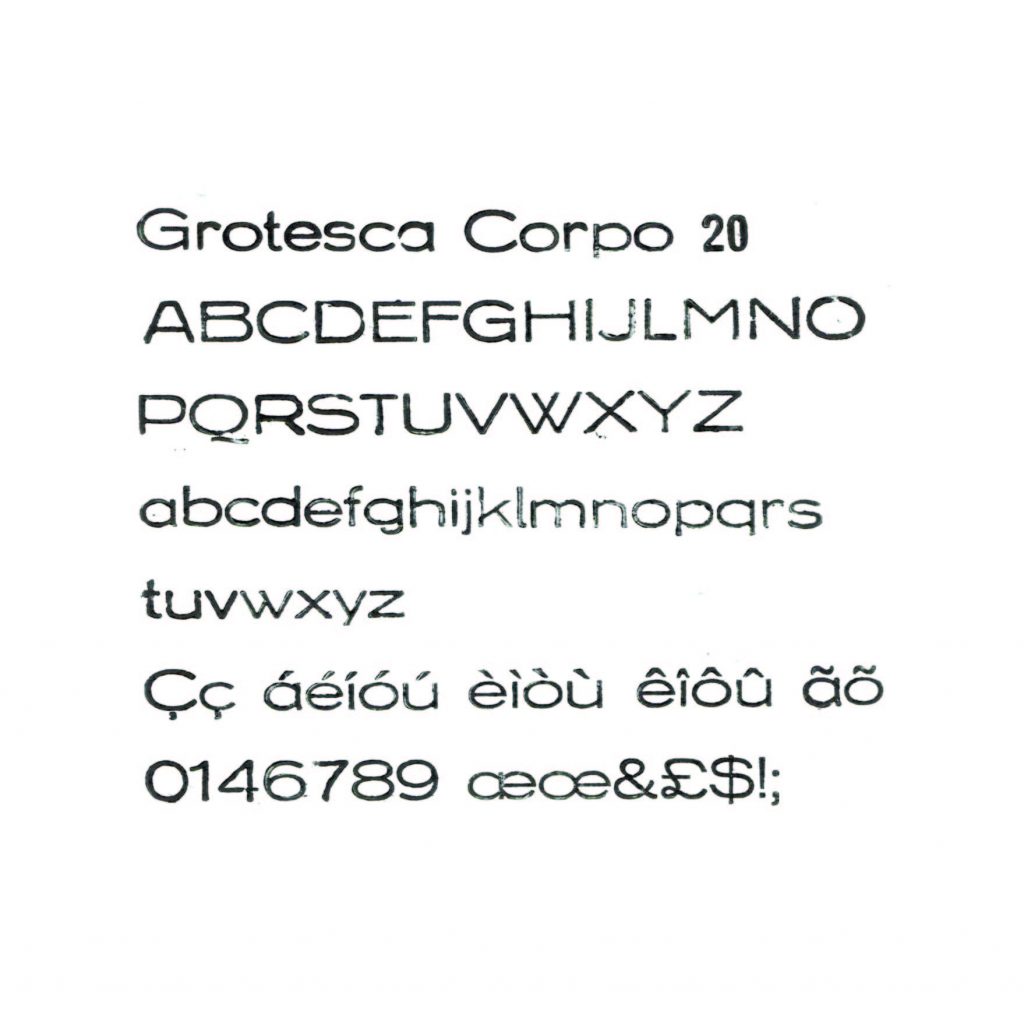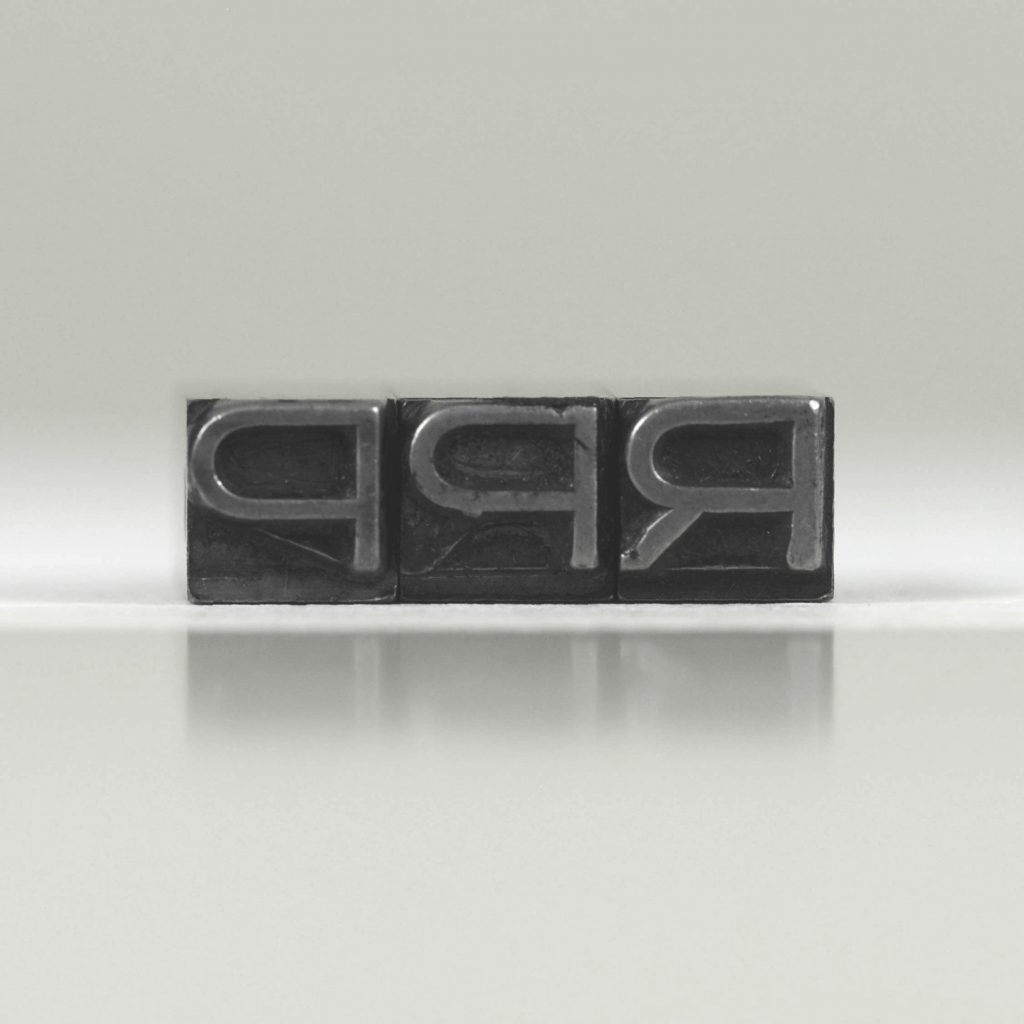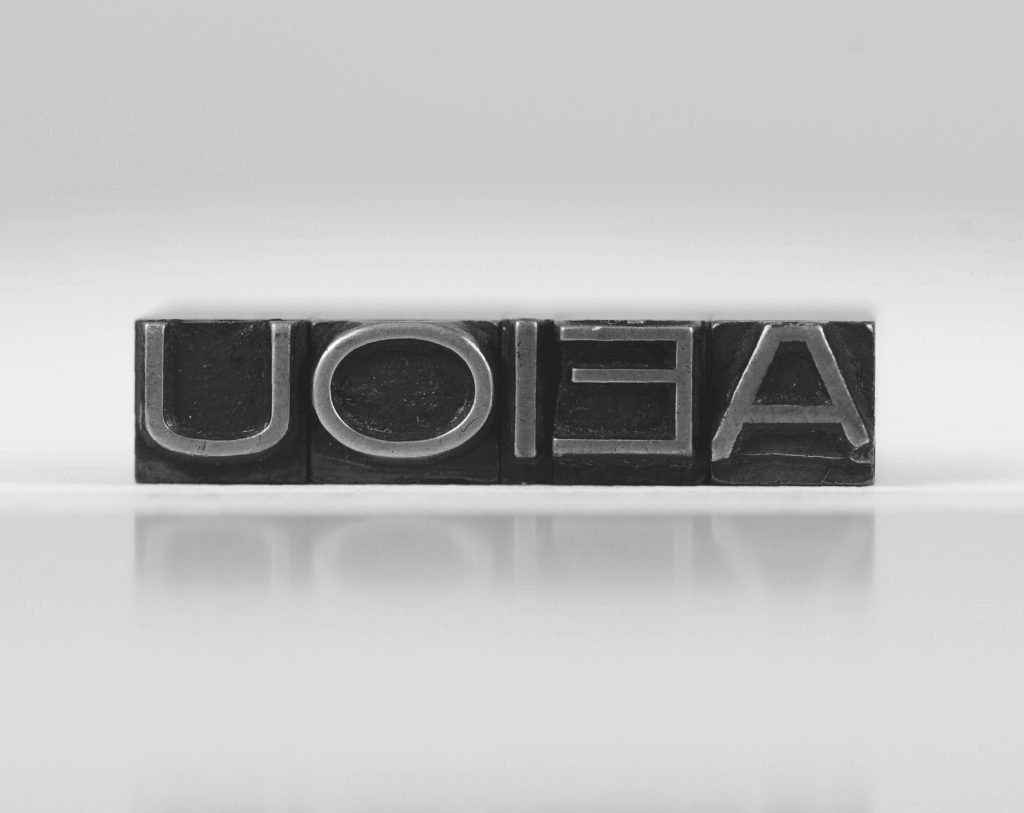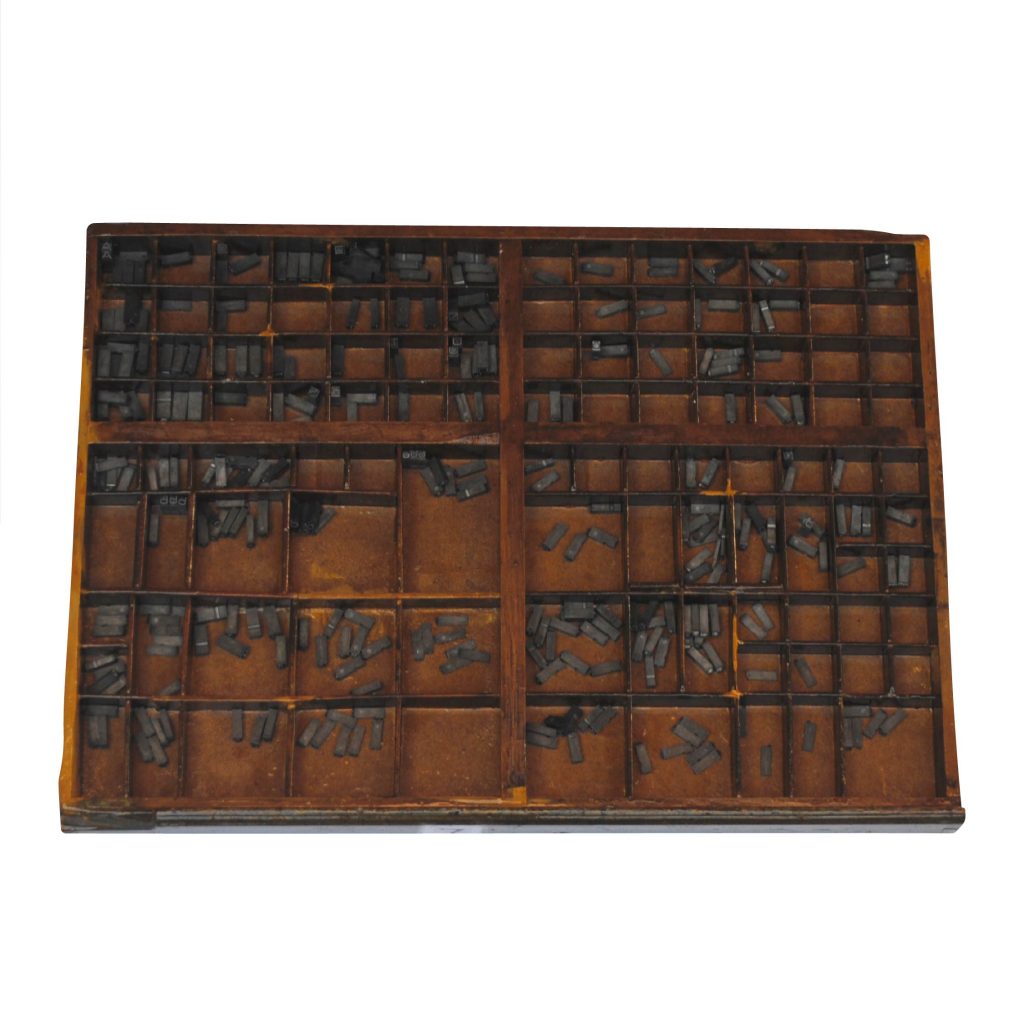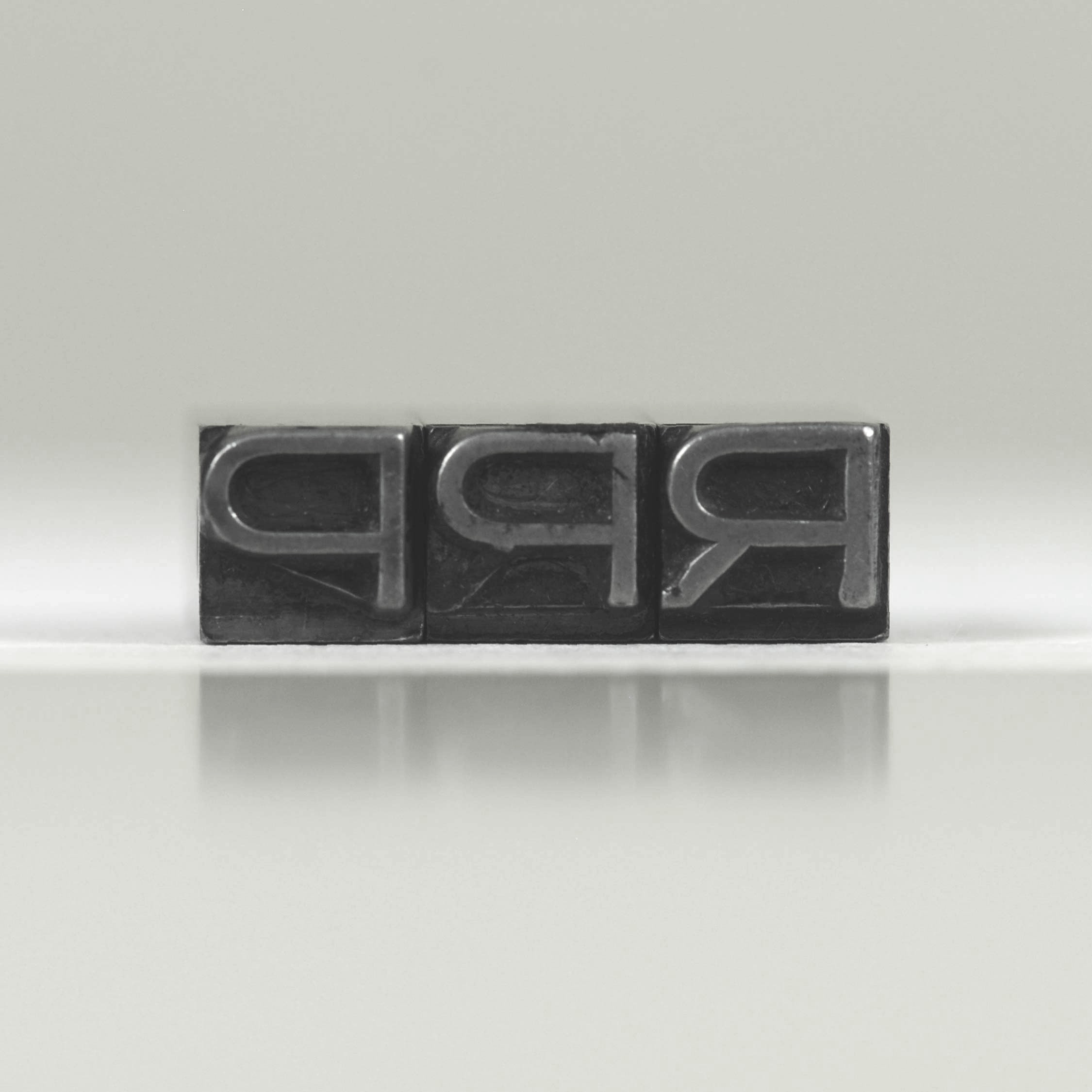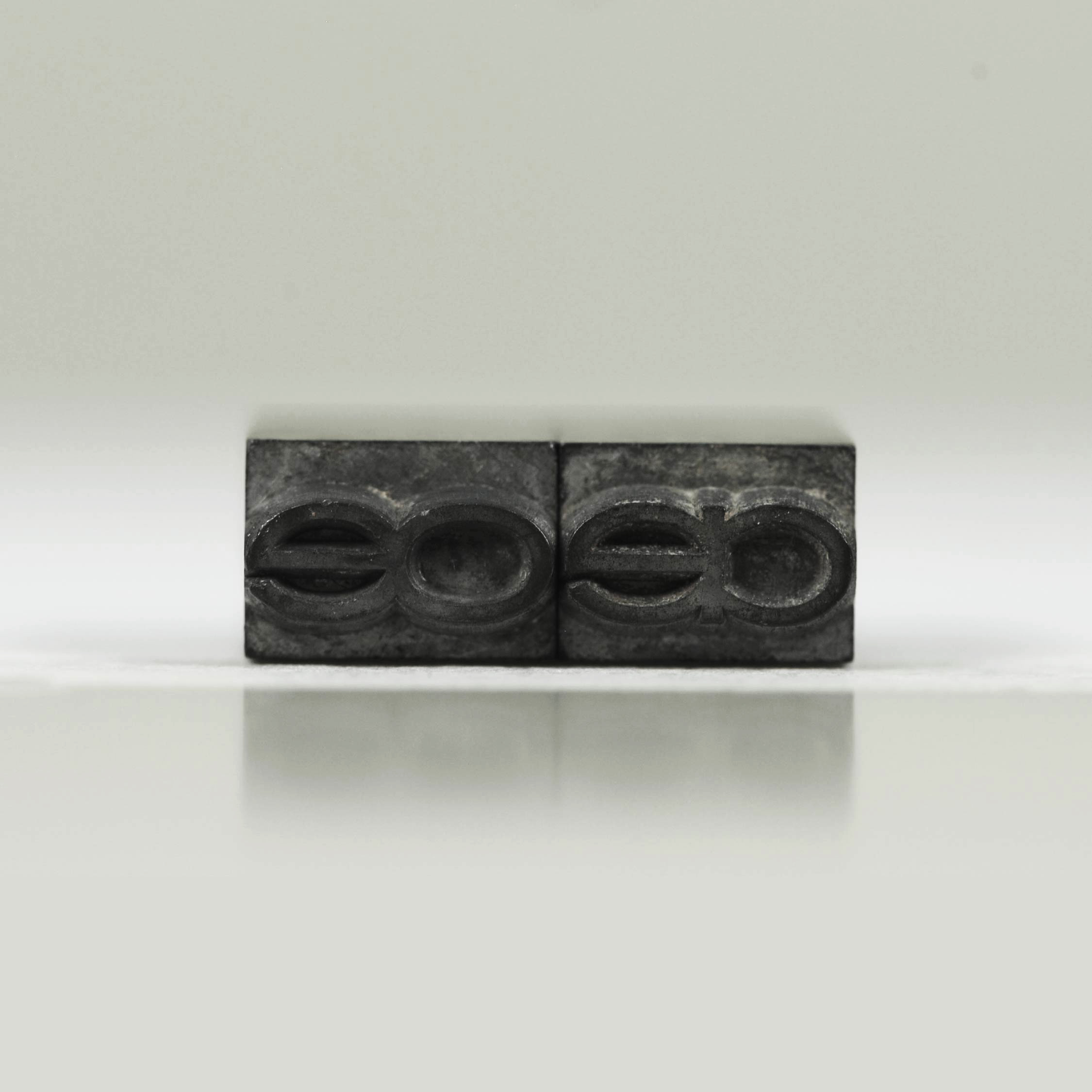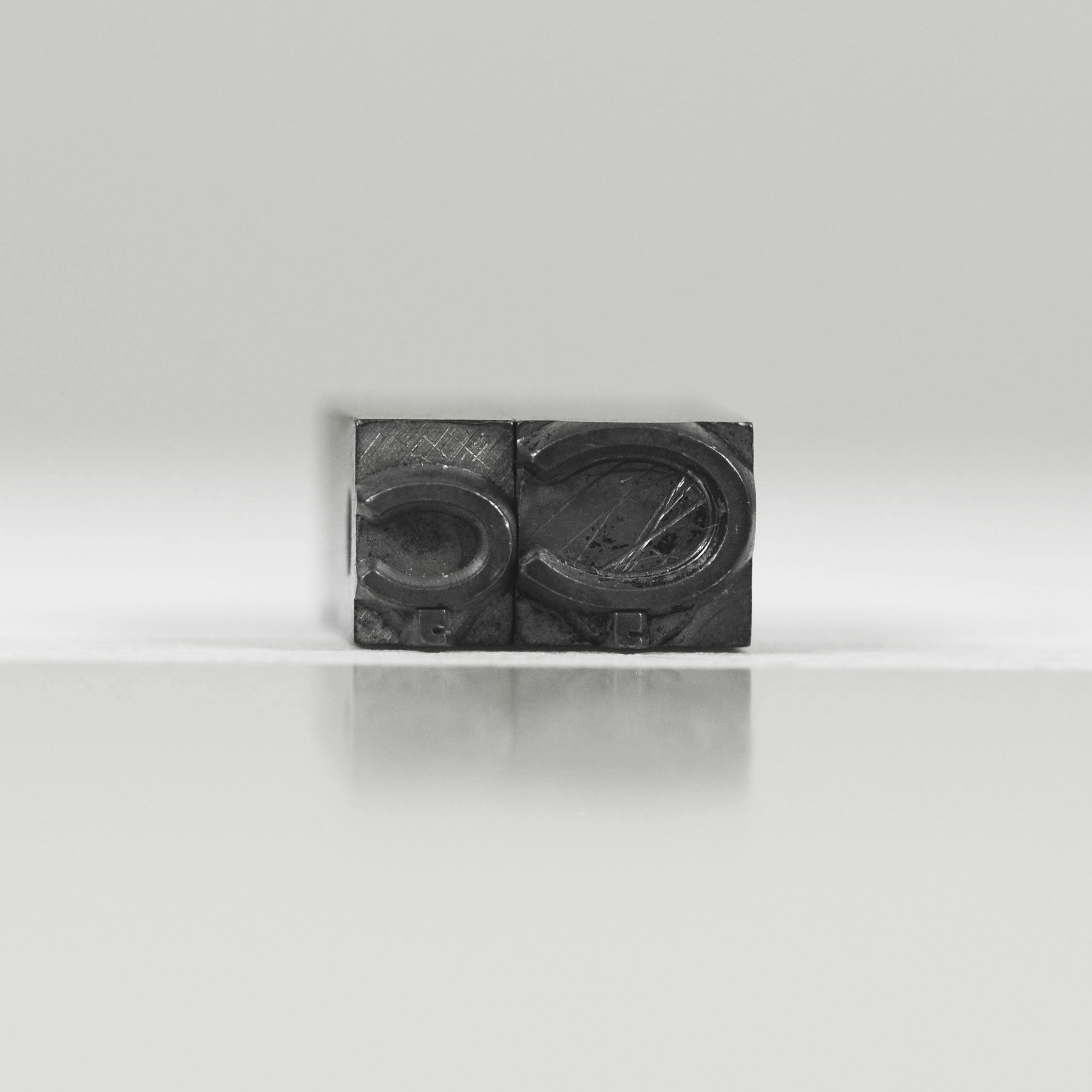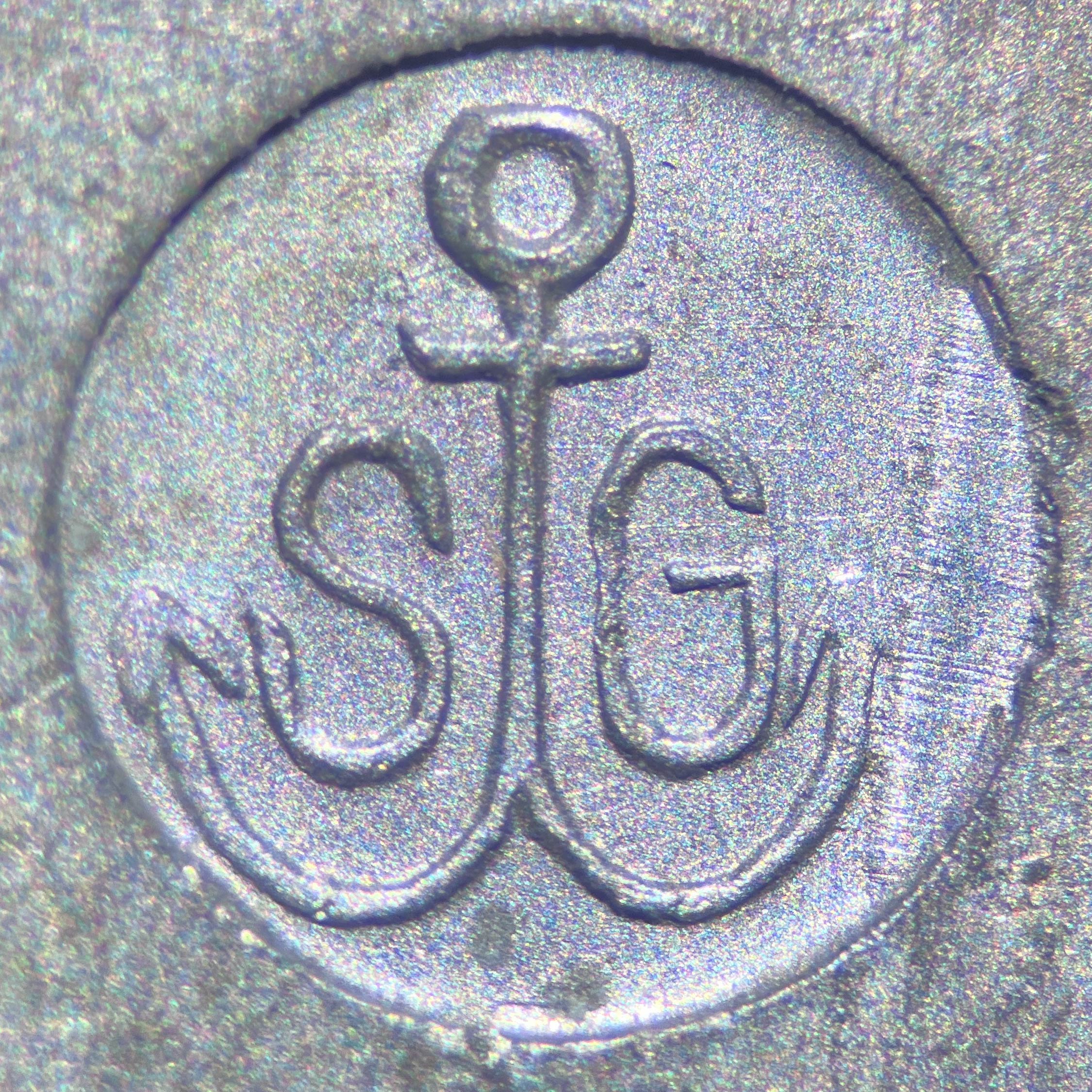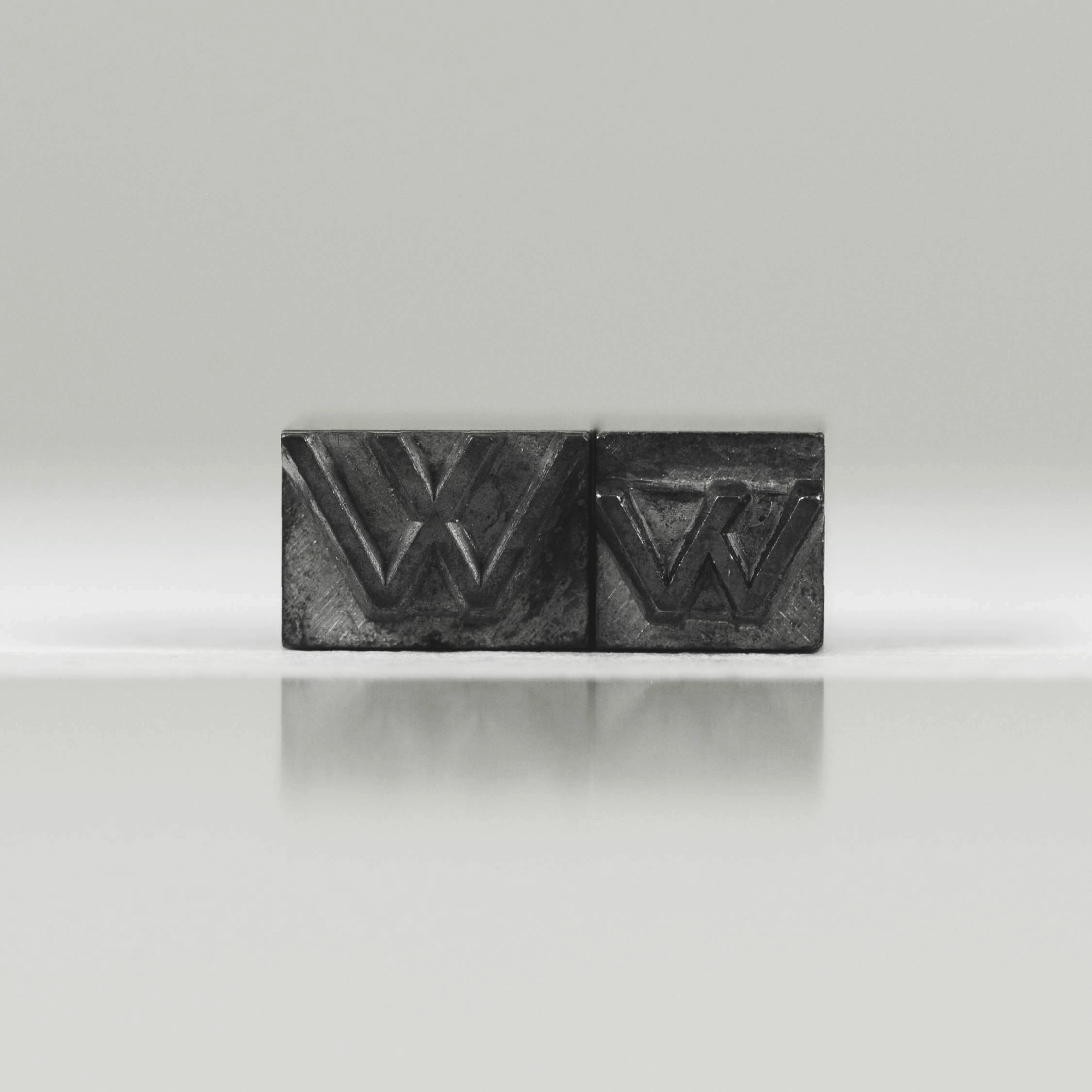
Ganz Breite Koralle 20pt
Estilo
Grotesca
Corpo (pt)
20
Caracteres Chave
B, Q, W, g
Fundidora
Schelter & Giesecke
Catálogo
Schelter & Giesecke, Schriftprobe [1940]
Tipo de Inscrição
Marca de fundidora
Localização da Inscrição
Face esquerda
Estado de Conservação
Regular; Há marcas de uso recorrente; alguns tipos apresentam desgaste na face que pode comprometer a qualidade da impressão.
Quantidade Total de Tipos
304
Disponibilidade
Maiúsculas | Minúsculas | Algumas minúsculas acentuadas | Quase todos os numerais | Ligaturas
Ausência de Caracteres
Falta a letra "K" maiúscula; sem maiúsculas acentuadas; faltam os numerais "2, 3 e 5".
Estes tipos foram identificados como Ganz Breite Koralle, da família Koralle, também da fundidora J.G. Schelter & Giesecke (1940), lançada em 1921 (Wetzig, 1926). No catálogo consultado (Schelter & Giesecke A.G., 1940, p. 174-175) há 15 variações da família Koralle. Ademais, a fonte Ganz Breite Koralle e outras da família foram utilizadas no contexto da Bauhaus (George e Coles, 2022), que valorizava formas geométricas, sobriedade e funcionalidade – características encontradas em fontes sem serifas e sem adornos.